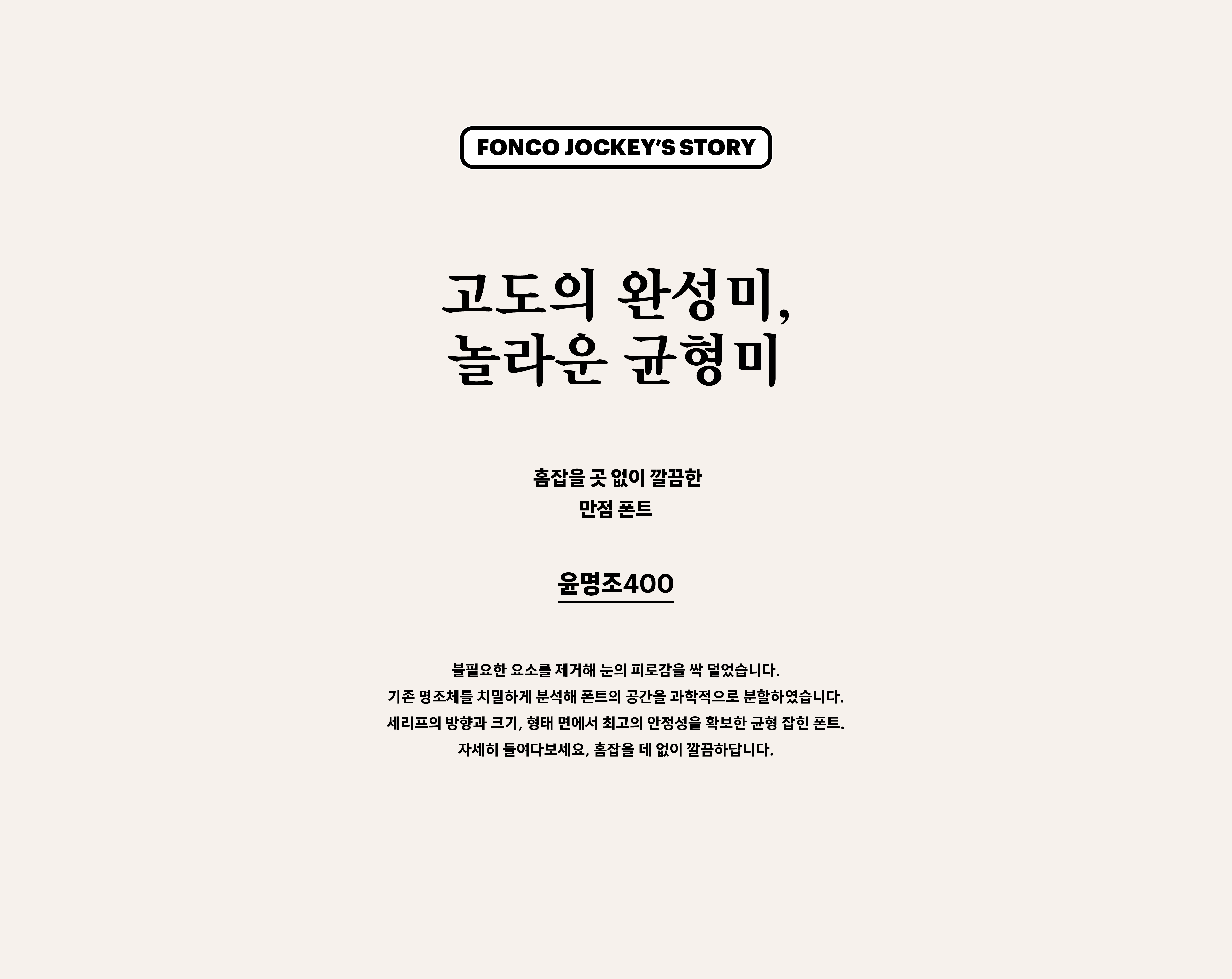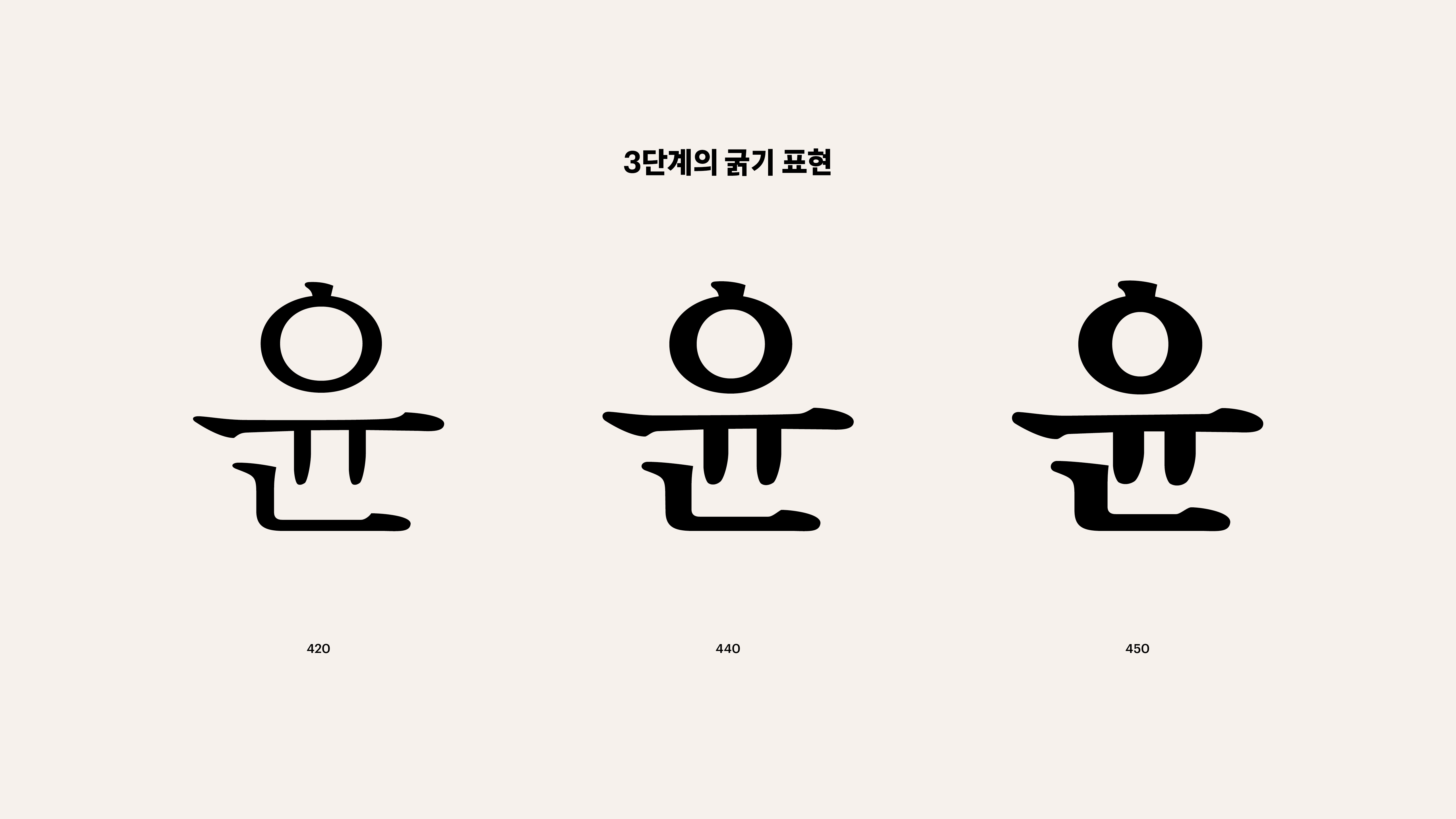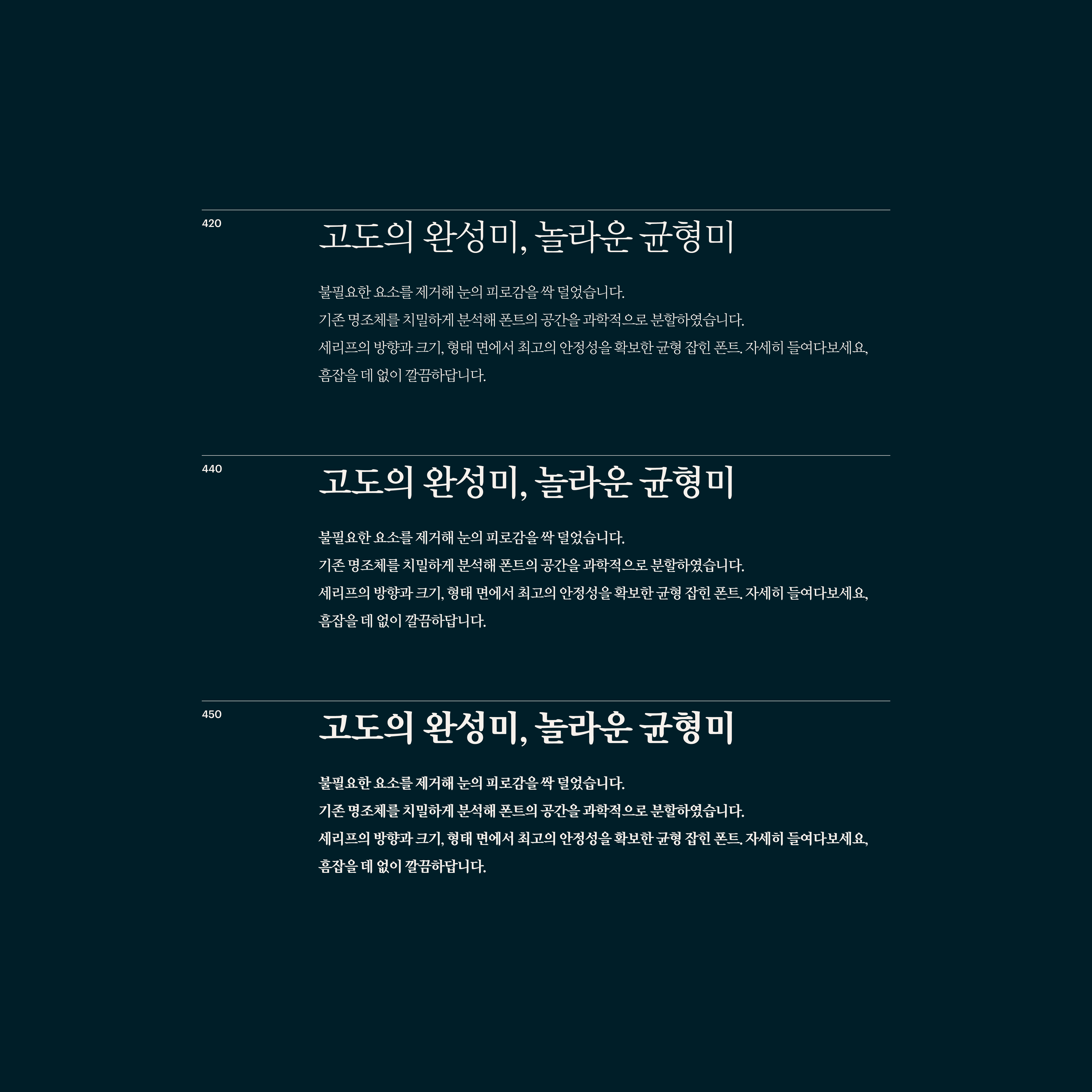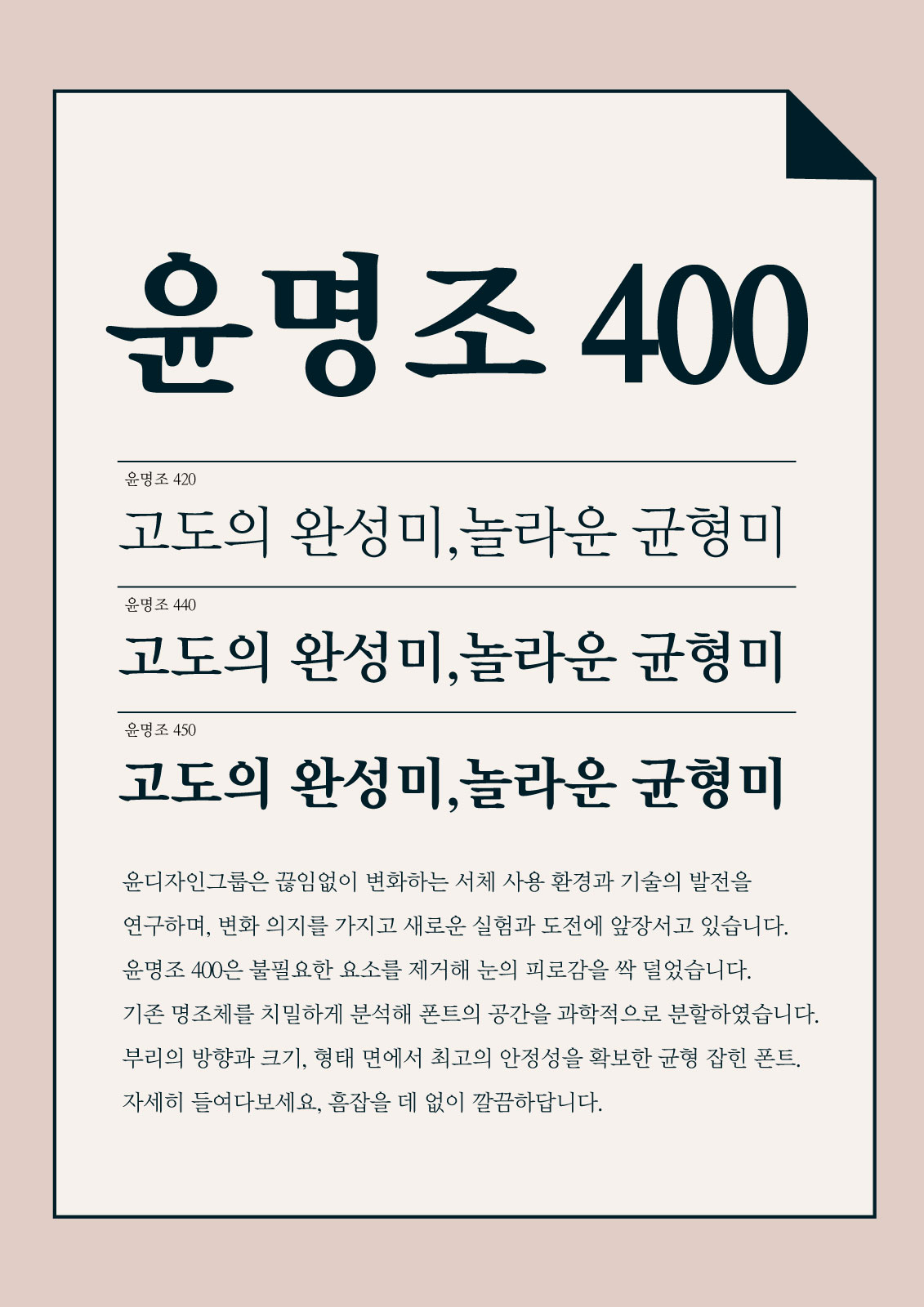
윤명조 400
2000-2004
Yoon 윤명조 400
불필요한 요소를 제거해 눈의 피로감을 싹 덜었습니다. 기존 명조체를 치밀하게 분석해 폰트의 공간을 과학적으로 분할하였습니다. 부리의 방향과 크기, 형태 면에서 최고의 안정성을 확보한 균형 잡힌 폰트. 자세히 들여다보세요, 흠잡을 데 없이 깔끔하답니다.